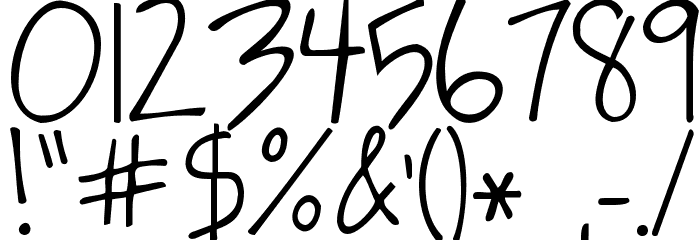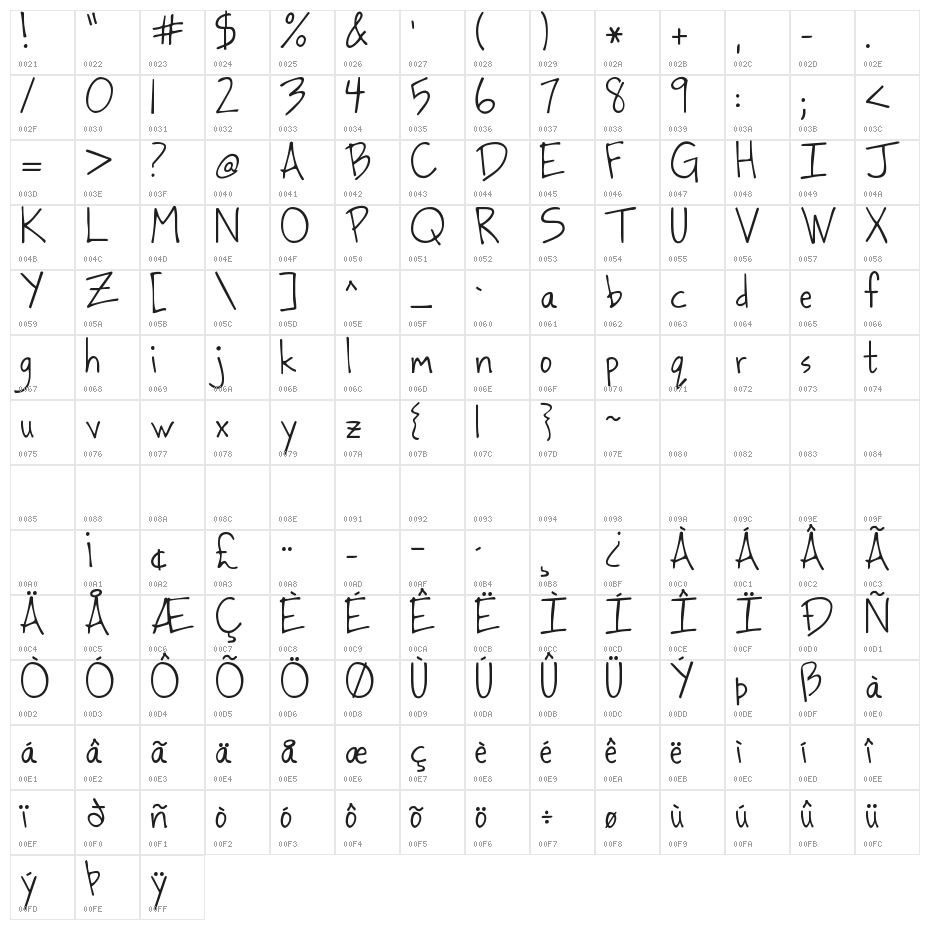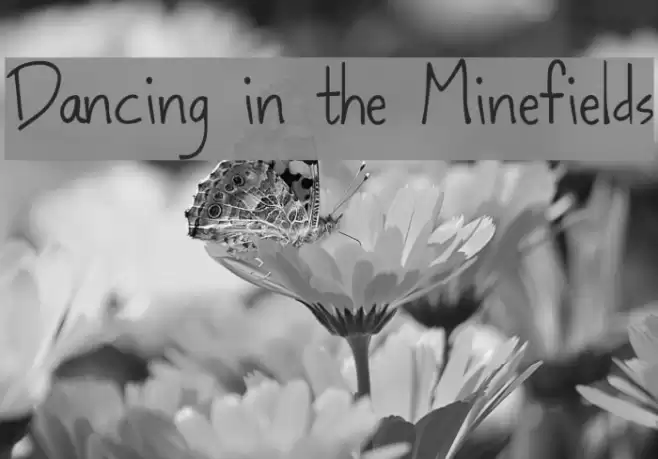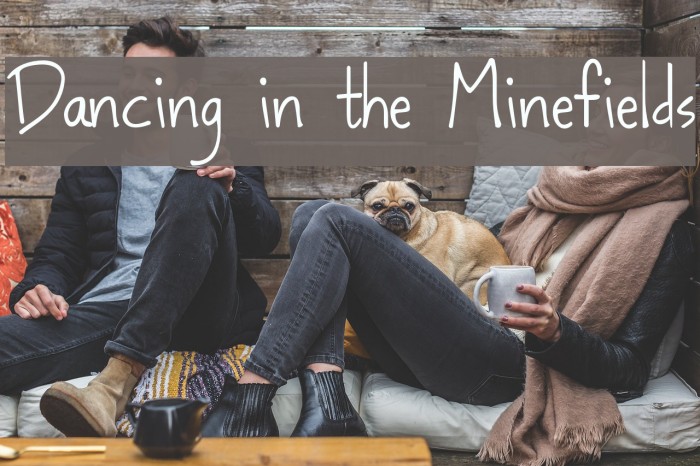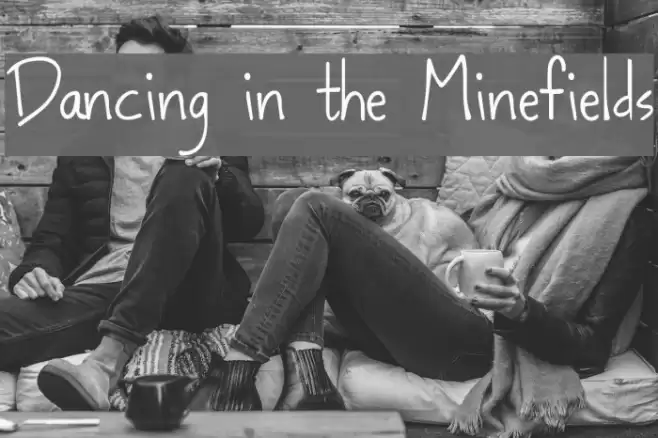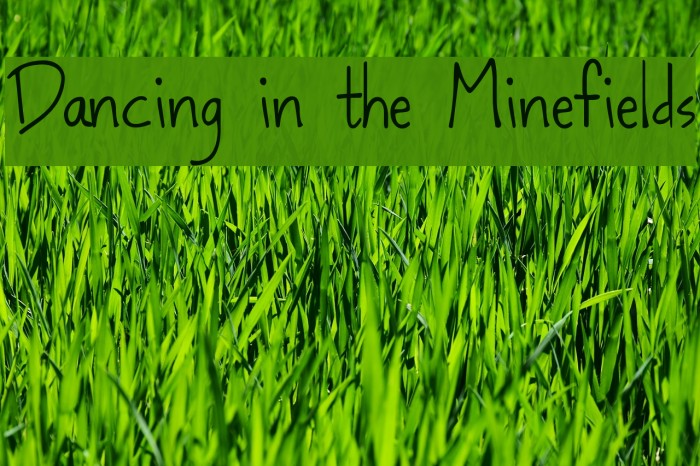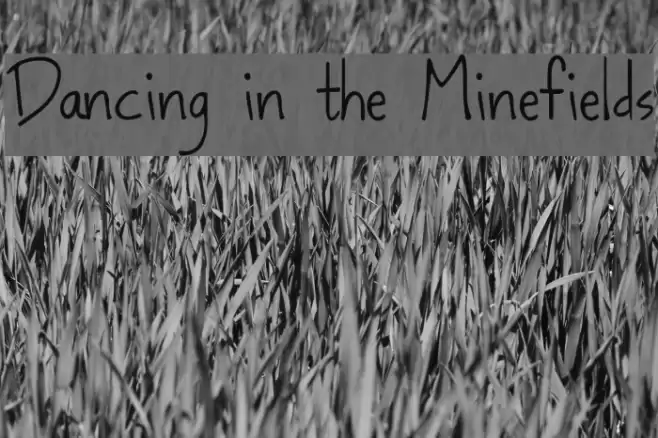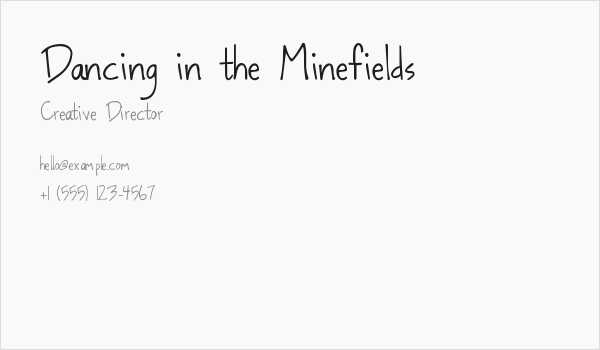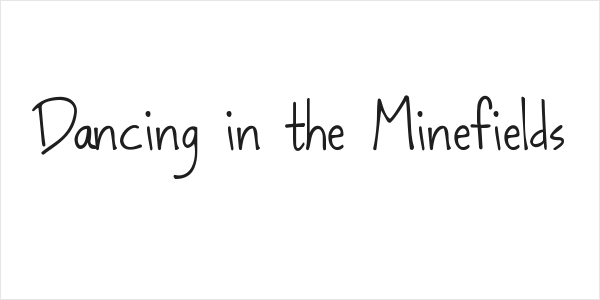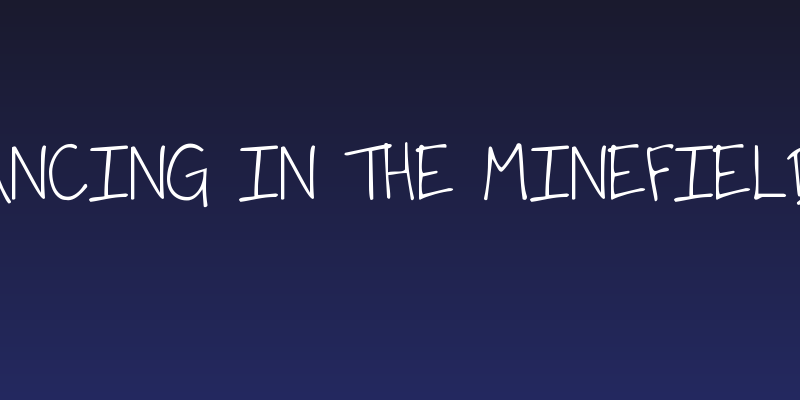
Dancing in the Minefields Font
| 全体的なスタイル | Casual, Playful |
| 用途 | Headlines, Informal text, Creative projects |
| おすすめプロジェクト | Ideal for greeting cards, children's books, personal blogs, and informal branding projects. |